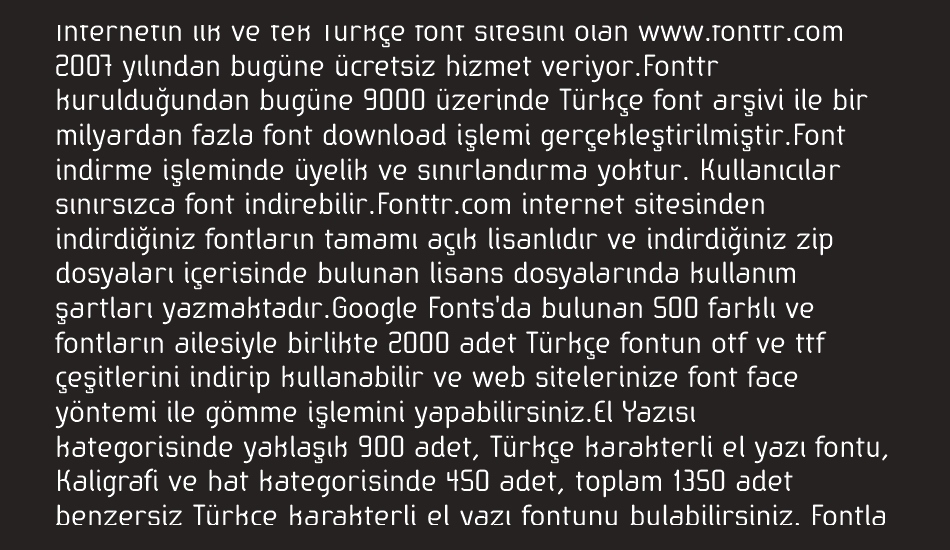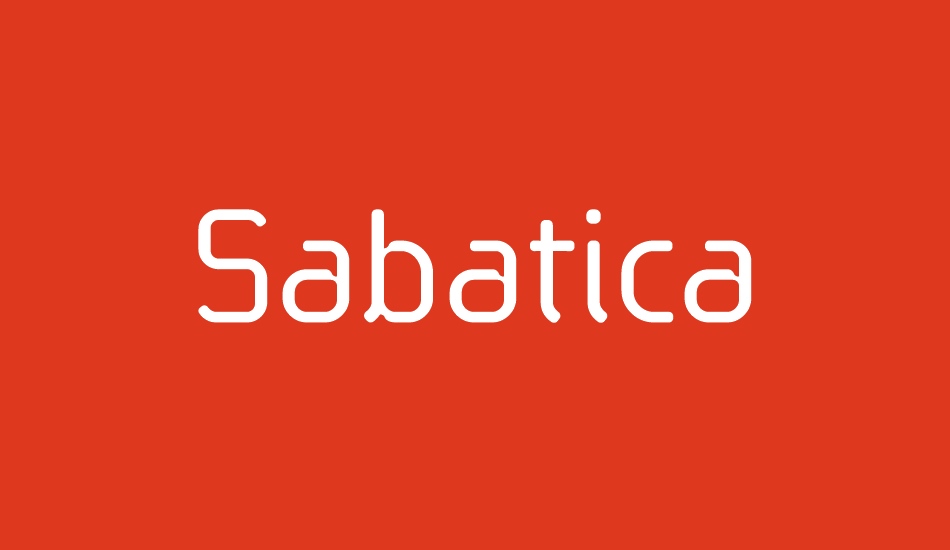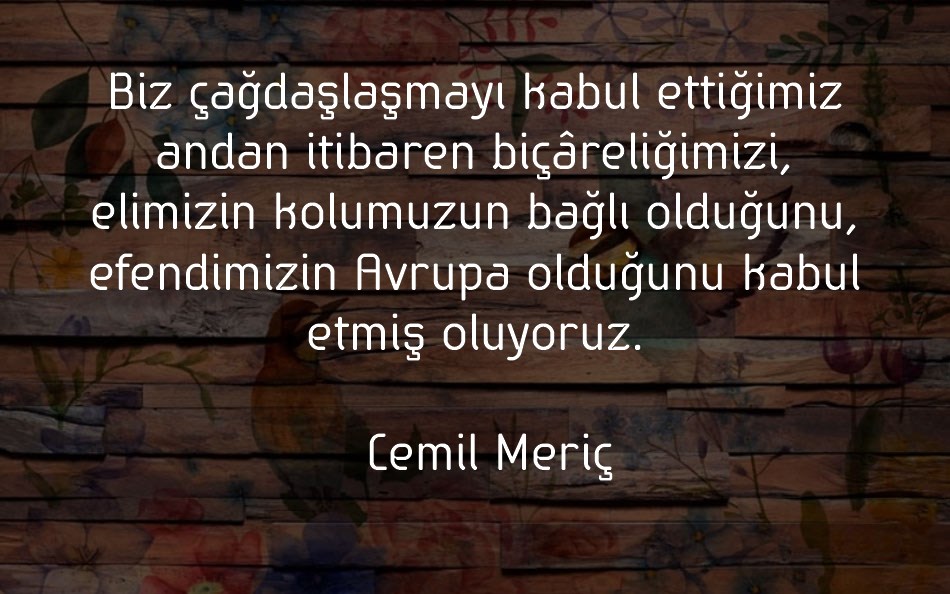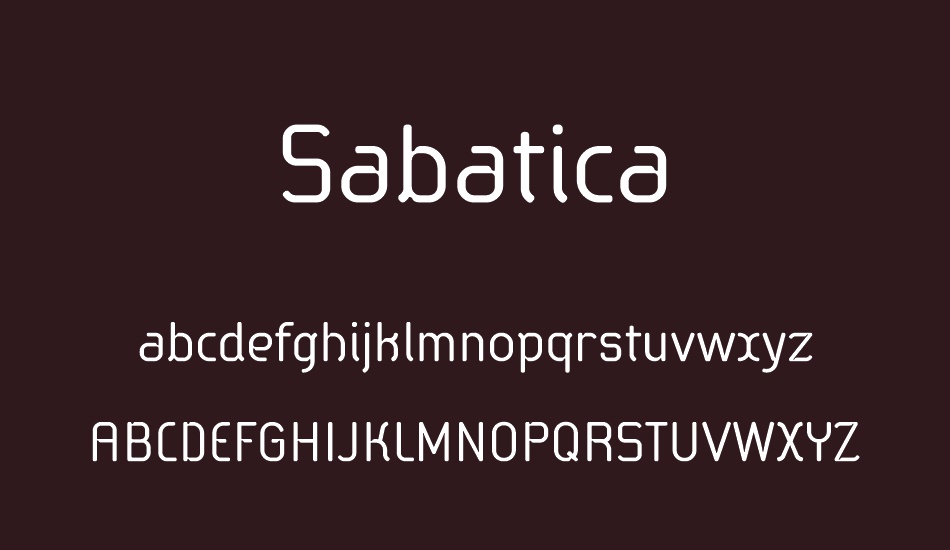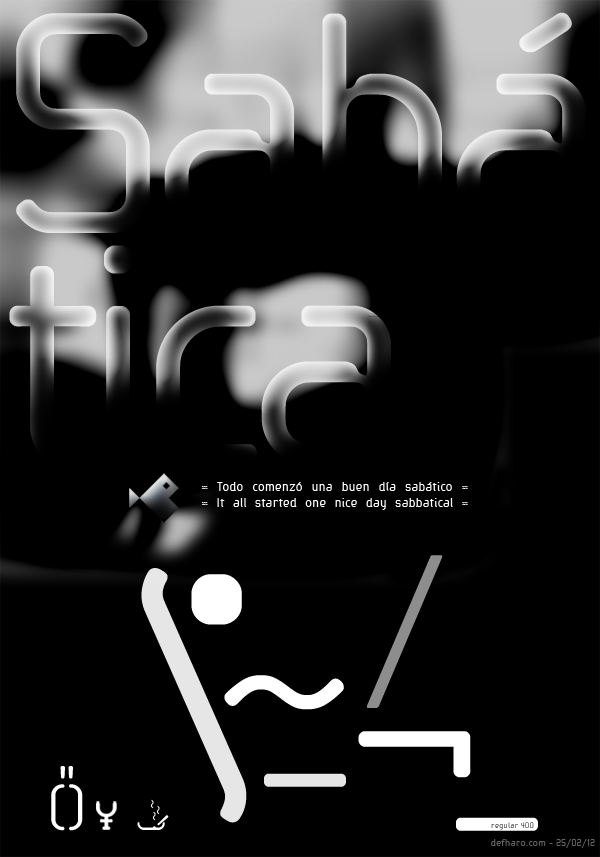
Sabática font
Sabática
Esta fuente la comencé a hacer un Sábado de Noviembre con tiempo libre y la he acabado también un sábado de febrero, de ahí su nombre: Sabática. Visita mi Web para conocer su historia.
This font began to make a Saturday in November with free time and I also finished a Saturday in February, hence the name: Sabática. Visit my website to learn its history. Here you can download a smaller version for use as WebFonts soon my site to download the full version for free.